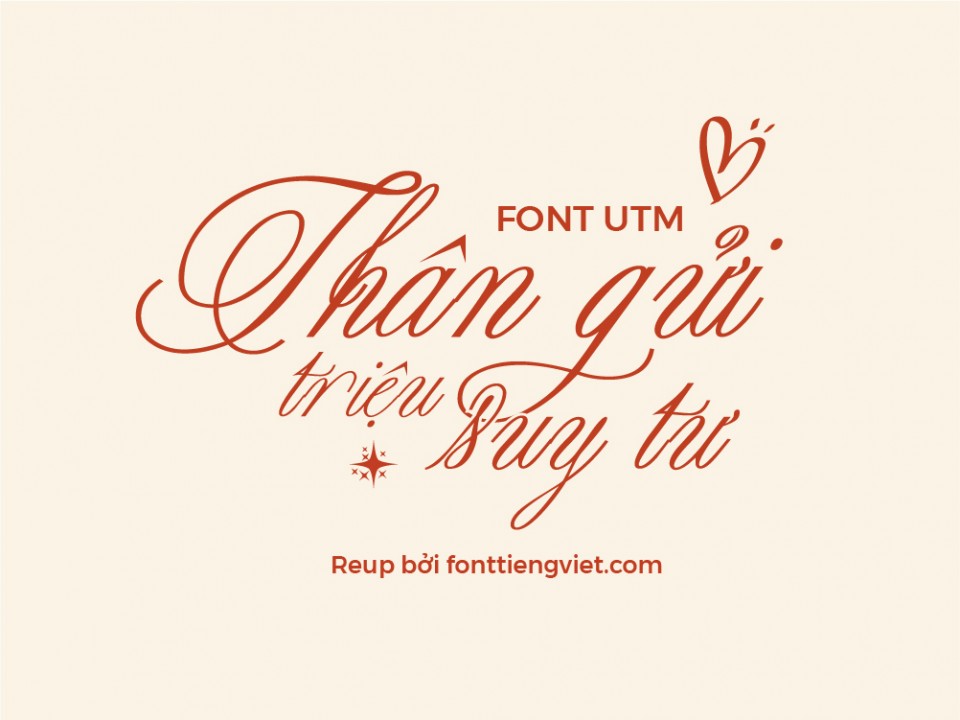
Font việt hóa UTM Yves KT ( 3 font )
Giới thiệu bộ Font việt hóa UTM Yves KT ( 3 font )
Trong thế giới thiết kế đồ họa chuyên nghiệp, việc lựa chọn một bộ Font Miễn Phí chất lượng luôn là ưu tiên hàng đầu của các nhà sáng tạo. Bộ Font việt hóa UTM Yves KT ( 3 font ) là một trong những lựa chọn tuyệt vời nhất dành cho những ai yêu thích phong cách thiết kế thanh lịch và hiện đại. Được phát triển dựa trên bộ mã UTM nổi tiếng, các ký tự trong bộ font này đã được tinh chỉnh hoàn hảo để hỗ trợ đầy đủ tiếng Việt, giúp người dùng không còn lo lắng về lỗi hiển thị dấu câu hay khoảng cách chữ không đều.
Đặc điểm nổi bật của bộ font
Bộ Font việt hóa UTM Yves KT ( 3 font ) bao gồm ba biến thể khác nhau, cung cấp sự linh hoạt tối đa cho nhiều loại dự án khác nhau. Với đường nét mảnh mai nhưng vẫn giữ được sự chắc chắn, bộ font này rất phù hợp để làm tiêu đề sách, thiệp mời đám cưới hoặc các ấn phẩm truyền thông sang trọng. Sự cân bằng giữa nét cổ điển và hơi thở đương đại giúp tác phẩm của bạn trở nên thu hút và chuyên nghiệp hơn trong mắt người xem.
Ứng dụng thực tế của Font việt hóa UTM Yves KT ( 3 font )
Nhờ tính ứng dụng cao, bộ font này được sử dụng rộng rãi trong các phần mềm thiết kế phổ biến như Photoshop, Illustrator hay Canva. Đối với các bạn học sinh và giáo viên, việc sử dụng font chữ này trong các bài thuyết trình hay thiết kế báo tường sẽ tạo nên một diện mạo mới mẻ, dễ nhìn và đầy tính thẩm mỹ.
Lưu ý khi sử dụng
Khi sử dụng bộ font này, bạn nên kết hợp với các tông màu trung tính hoặc pastel để làm nổi bật sự tinh tế của các nét chữ. Hãy đảm bảo rằng khoảng cách dòng được điều chỉnh hợp lý để tối ưu hóa trải nghiệm đọc cho người xem.
Kết luận về bộ font